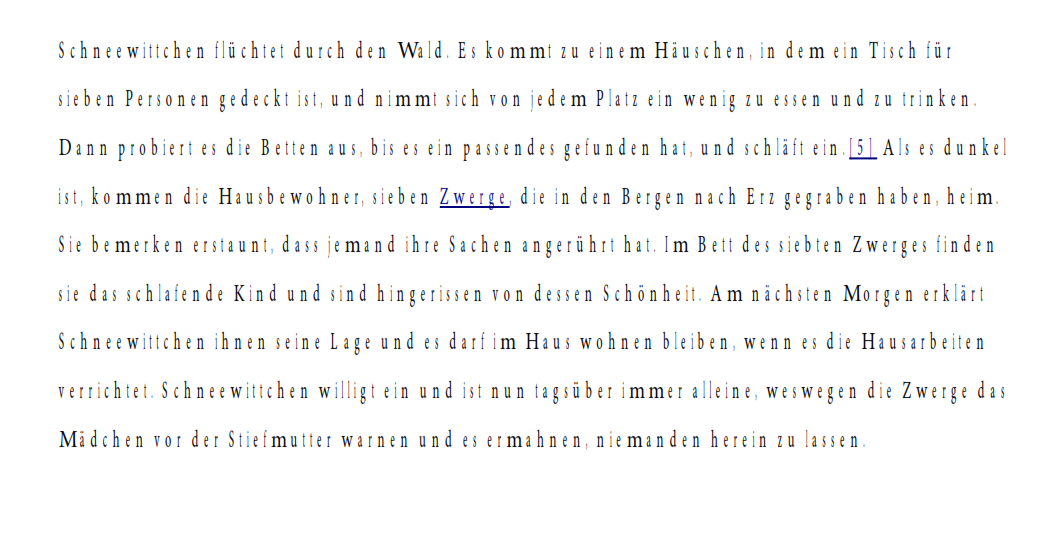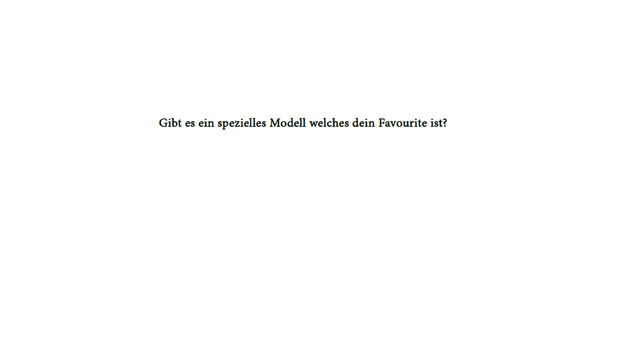
Minion-Variante für Bildschirmanzeige
vorab erstmal danke für all die informativen Beiträge hier im Forum. Ich habe schon ein gutes Stück zu dem mir bisher gänzlich fremden Themenfeld Typografie lernen können.
Ich finde die Myriad Pro/Minion Pro Kombi für ausgedruckte wissenschaftliche Arbeiten super, nur habe ich das Gefühl, dass der Fließtext in Minion Pro bei Arbeiten, die für die Darstellung auf dem Bildschirm gedacht sind, etwas dünn wirkt und somit ein bisschen schwerer zu lesen ist. Gibt es eventuell eine ein Ticken fettere Variante der Minion Pro, die sich auf dem Bildschirm besser macht?
Wenn Du für Bildschirm-Darstellungen unbedingt bei der Minion bleiben willst und denkst, dass es ein stärkerer Schnitt tut, warum nimmst Du dann nicht einfach den nächst stärkeren Schriftschnitt? Also Minion auf Minion Medium, etc.
Andere Frage: in welcher Form willst Du Deine Inhalte denn überhaupt digital publizieren? Möchtest Du beispielsweise die Minion auf einer Webseite einbinden, würde ich Dir die dafür optimierte Minion Web (Pro) nahelegen.
Es geht nur um Hausarbeiten, die man per Email verschickt und von denen man weiß, dass sie der Dozent nicht ausdrucken wird sondern am Bildschirm lesen...
Als PDF? In Word? ...?
Das Feld der Bildschirmdarstellungen ist natürlich riesig. Da spielen dutzende Faktoren mit rein, wie die Schrift am Ende auf einem bestimmten Gerät in bestimmter Größe in einem bestimmten Programm aussieht. Bei einem PDF in Minion sehe ich eigentlich keine größeren Leserlichkeitsprobleme, die man unbedingt umschiffen müsste.
Jetzt kann ich die Frage etwas spezifizieren: Ein in Minion Pro verfasstes Dokument wird nicht in allen pdf readern richtig angezeigt bzw. nur im acrobat reader richtig angezeigt. Was kann man da machen? Ich kann den Empfängern der PDF schlecht sagen, dass sie sich einen bestimmten pdf reader runter laden sollen, damit sie meinen Text lesen können. Und ist es normal, dass "gefettete" Wörter leicht verschwommen aussehen so als hätte man Tinte benutzt?
Ja hab Sie eingebettet. Also denke zumindest dass ich das getan habe. Ich habe einen Screenshot von "Nicht richtig angezeigt" gemacht:)